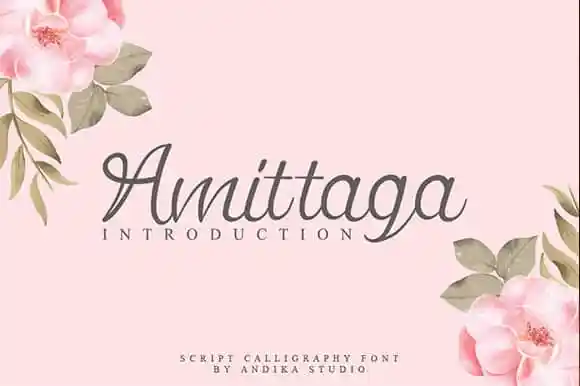
Amittaga Script Font – Download Grátis
A Amittaga Script Font é a nova tendência nas letras tipográficas, perfeitamente adaptada para aplicações variadas no design visual. Suas formas elegantes e sofisticadas são perfeitas para uso em exposições de paredes, embalagens, logotipos de redes sociais, publicidade e até mesmo como uma marca distintiva na fotografia ou nos selos de água. A Amittaga Script é versátil o suficiente para se tornar um aliado valioso em projetos que exigem o toque pessoal da escrita a mão. Ideal tanto para criações de produtos quanto para as mais variadas aplicações gráficas, desde os cartões de visita até os e-mails de marketing personalizados. Seja você uma marca ou um designer, a Amittaga Script oferece a oportunidade de deixar sua marca com estilo e elegância.